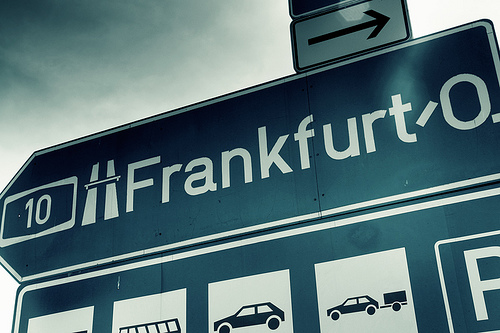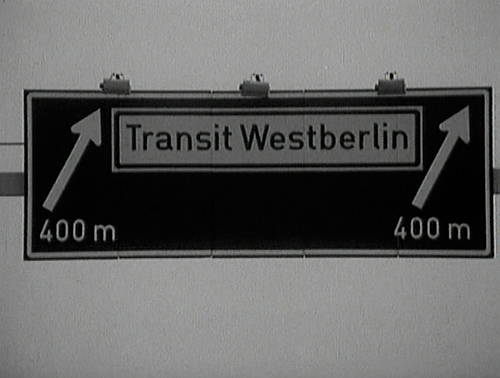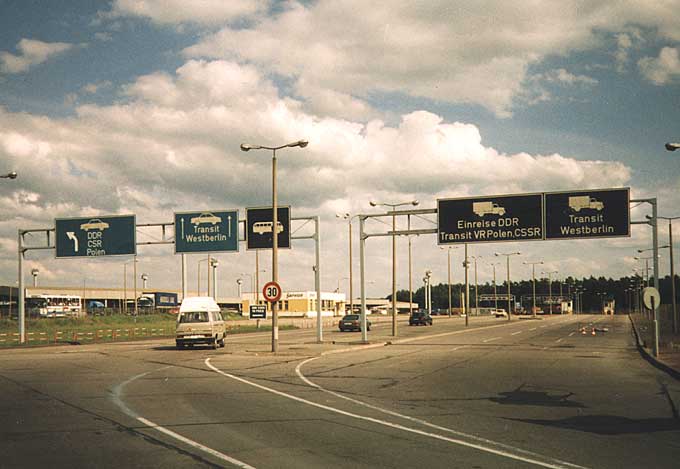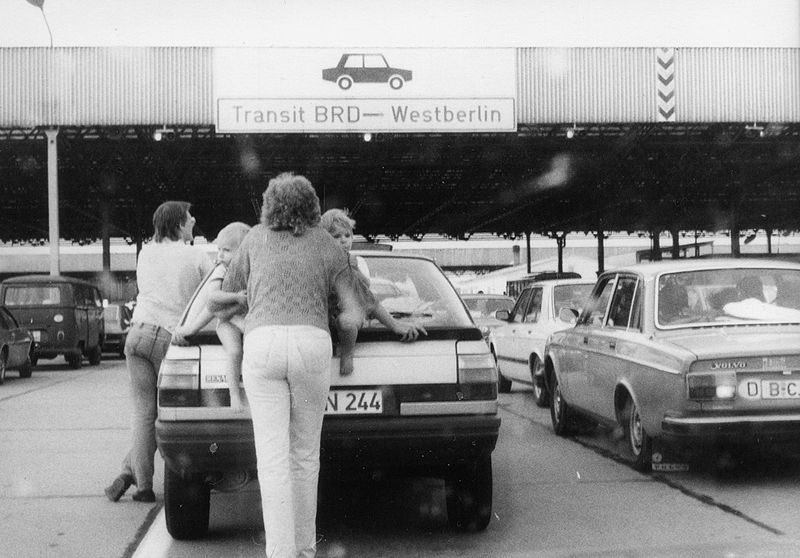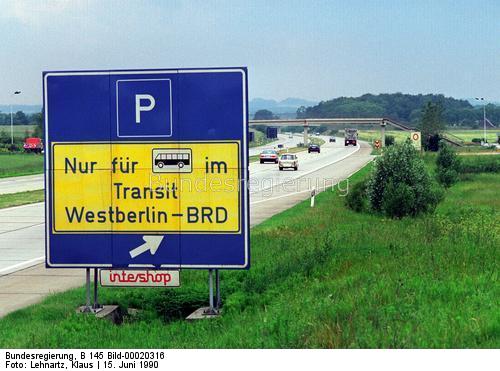
Alte Verkehrsschilderfotos aus der DDR
»Er?tes ?oziali?ti?ches Dorf« in »Schaftstiefelgrotesk« — da werden einge Leute mal wieder ihre Vorurteile an der Realität überprüfen können. :wink:
Dieses Bild ist doch für die Zeit bis 1940 viel zu neu. Eisenhüttenstadt wurde erst später als Vereinigung von Stalinstadt und Fürstenberg gegründet, also zu Zeiten der DDR.
Das hatte mit dem ursprünglichen Thema nix zu tun. Hab mich nur über die historischen Verkehrsschilder unter dem angegebenen Link gefreut. Deshalb schrieb ich, dass da auch was FÜR MICH dabei ist.
Auch was für mich dabei!
Sehr schön! Ich wusste gar nicht, dass DDR-Ortsschilder mal so aussahen. Wenn du mehr in der Richtung hast, immer her damit! :cheer:
Das Fotos des Eisenhüttenstadtschilds ist ja geradezu subversiv. Herrlich! (Da die Übermalung so offensichtlich ist, springt einen der frühere Stadtname Stalinstadt geradezu an. Das erinnert mich an das Propagandagedicht »Die ewige Inschrift«, das in DDR-Lesebüchern stand.)
Auch was für mich dabei!
Sehr schön! Ich wusste gar nicht, dass DDR-Ortsschilder mal so aussahen.
Nicht offiziell. Der Standard seit den 1970ern war eine Gill Sans
Es überlebte aber auch jede Menge (alte) DIN bis zur Wende:
… das Propagandagedicht »Die ewige Inschrift«, das in DDR-Lesebüchern stand.
Kenne ich gar nicht. Das muß vor meiner Zeit gewesen sein. Ober nach meiner (Schul)zeit. Nicht mal Google scheint das Gedicht zu kennen.
Der Standard seit den 1970ern war eine Gill Sans …
Es war nicht alles schlecht. :|
Aber im Ernst: Die Gill für Straßenschilder war zumindest ästhetisch eine überzeugende Lösung. Vermutlich sind modernere Schriften besser lesbar, auch ist Gill schmal problematisch, aber alles in allem macht sie einen freundlicheren Eindruck. Da fährt man gleich viel gelassener. :D
»Er?tes ?oziali?ti?ches Dorf« in »Schaftstiefelgrotesk« — da werden einge Leute mal wieder ihre Vorurteile an der Realität überprüfen können. :wink:
Siehe dazu auch dieses Foto :D Danke nochmal an Thorsten für den Tip – riesengroß sind die Bilder nicht, aber es sind einige echt schöne dabei, auch genau solche die ich gesucht habe :D Bin immer noch dabei, mich da durch zu arbeiten, bevor ich mich den anderen Links zuwende jump.gif
Auch was für mich dabei!
Hier ist noch eins ...
:) schön ... zufällig auf Anhieb erkannt: das ist etwa 20km von wo ich lebe, in Feldkirch, die Brücke über die Ill.
Sieht heute ganz anders aus - vor allem hätten die Linksalternativen aus dem Jugendclub gleich nach der Brücke das "Reichsgrenze" längst typografisch neu gestaltet.
Sehr schön! Ich wusste gar nicht, dass DDR-Ortsschilder mal so aussahen.
Nicht offiziell. Der Standard seit den 1970ern war eine Gill Sans[/quote:2lshthws]
An den erinnere ich mich natürlich. Gab’s dann vor 1970 keinen Standard?
Es überlebte aber auch jede Menge (alte) DIN bis zur Wende
Waren die blauen Autobahnschilder nicht generell in DIN, zumindest an den Transitautobahnen? (Wurde das hier schon mal diskutiert?) In meiner Erinnerung waren die blauen Schilder am Berliner Ring und der Strecke Richtung Marienborn (für Wessis: der heutigen A2), auf der der elterliche Trabi oft unterwegs war, jedenfalls nie in Gill Sans. Sollten die 1990 schon alle über 20 Jahre alt gewesen sein?
Ich lasse mich natürlich gern eines besseren belehren. Leider konnte ich keine DDR-Fotos finden, auf denen die blauen Schilder zu sehen waren. Als Ersatz vielleicht das hier (Mischung DIN, Gill Sans?):
(der interessante Teil wird nach einem Klick auf das Bild sichtbar)
Gab’s dann vor 1970 keinen Standard?
Vorher gab’s auch DIN und natürlich viel Schildermaler-mäßiges, wie man ja in den Abbildungen oben sieht.
Waren die blauen Autobahnschilder nicht generell in DIN, zumindest an den Transitautobahnen?
Offenbar, obwohl sie in der StVO in Gill Sans abgebildet waren. Warum, konnte ich bisher auch nicht rausbekommen.
Michendorf, Berliner Ring: (steht immer noch)
Offenbar, obwohl sie in der StVO in Gill Sans abgebildet waren. Warum, konnte ich bisher auch nicht rausbekommen.
Ich hätte gedacht, ich hätte hier (oder doch woanders?) mal was davon gelesen, dass es mit der westdeutschen Finanzierung der Transitstrecken zu tun gehabt haben könnte. :?
Michendorf, Berliner Ring: (steht immer noch)
Das kann kein altes Schild sein. (Der Berliner Ring ist erst seit der Vereinigung BAB »10«. Dass die »10« nachträglich angebracht wurde, erscheint unwahrscheinlich.)
Ich glaube dir natürlich, was die anderen Parameter angeht, die für eine DDR-Herstellung sprechen. Ich tippe bei beiden Schildern auf die Übergangszeit 1990/91. Es hat ja eine Weile gedauert, bis alles umgestellt war. DDR-Kennzeichen (Muster IAB 1-23) wurden ja auch noch bis irgenwann 1991 ausgegeben (oft aber schon in DIN-Schrift).
Noch ein paar Fundstücke von der DDR-Seite der Grenze: